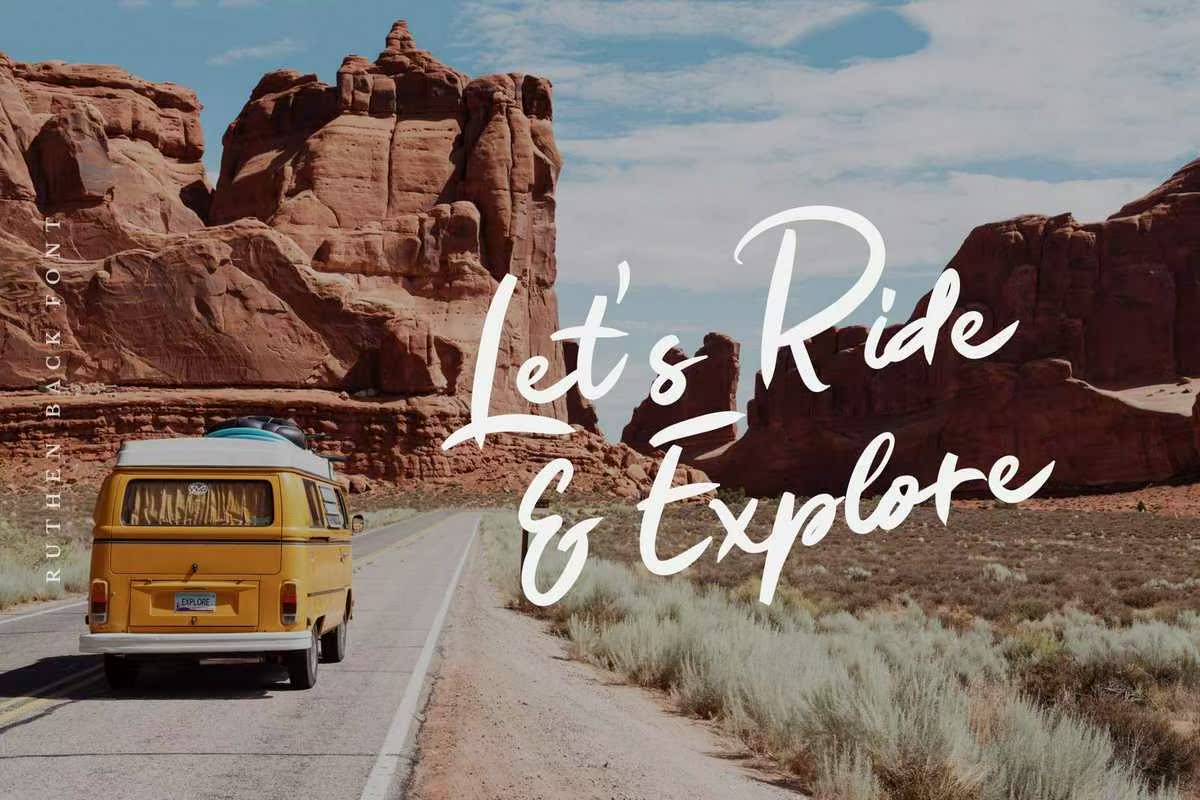
RuthenBack提供其他字体的不同格式,脚本字体带有TastelikeSignatures字体,因为所有字符都带有样式签名。在您的业务中,您的字体通常会被标记为个人品牌或商标。该字体还可以承受其他项目,如贺卡、书名簿/杂志、海报、,NEONLIGHT LOGO和TC.RuthenBack提供了与其他字体不同的速记格式,脚本字体带有趣味签名字体,因为这些字体都是基于样式签名的字符。这种字体在您的业务中通常会对您的人名品牌或logype造成负面影响。该字体还可用于其他项目,如贺卡、书名簿/杂志、海报、,NEONLIGHTLOGONDETC。